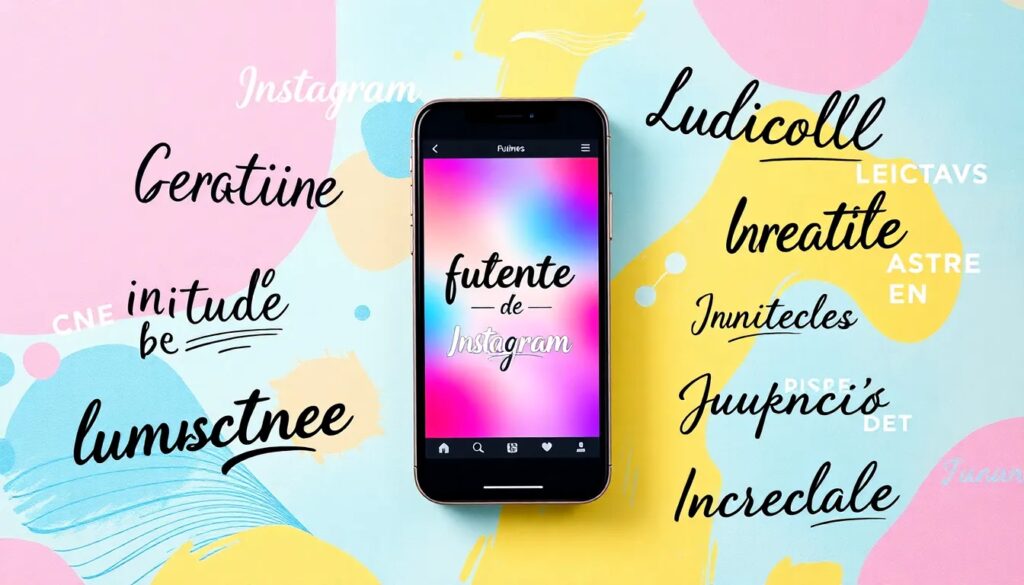
Instagram fonts: generador de fuentes para tus publicaciones
El uso de instagram fonts se ha convertido en una tendencia clave para quienes buscan destacar en esta red social. Las fuentes creativas no solo aportan un toque único a tus publicaciones, sino que también reflejan tu personalidad y estilo.
En este artículo, exploraremos todo lo que necesitas saber sobre las fuentes de Instagram, los generadores disponibles y cómo utilizar estos recursos para mejorar tu perfil y publicaciones.
¿Qué son las fuentes de Instagram?
Las fuentes de Instagram son variaciones tipográficas que los usuarios pueden utilizar para personalizar sus textos en esta plataforma. A través de diferentes estilos, puedes darle un aspecto más atractivo y único a tu contenido.
Estas fuentes se generan frecuentemente mediante caracteres Unicode, que permiten crear textos que simulan diferentes estilos de escritura. Esto incluye fuentes cursivas, negritas y otros efectos visuales.
Usar fuentes creativas en Instagram no solo mejora la estética de tu perfil, sino que también puede aumentar la interacción con tus publicaciones, ya que llamarán más la atención de tus seguidores.
¿Cómo funciona un generador de fuentes para Instagram?
Un generador de fuentes para Instagram es una herramienta que permite transformar texto ordinario en estilos tipográficos únicos. Simplemente ingresas el texto deseado y la herramienta te proporcionará diferentes opciones de fuentes.
La mayoría de estos generadores utilizan el estándar Unicode, lo que significa que los estilos generados son compatibles con diversas plataformas, no solo con Instagram. Esto facilita el uso de los textos en otras redes sociales o aplicaciones de mensajería.
El proceso es sencillo: ingresas tu texto, eliges el estilo que más te gusta y copias el resultado para pegarlo en tu perfil o publicaciones. Algunos generadores incluso ofrecen opciones de personalización más avanzadas.
¿Cuáles son las fuentes más populares para Instagram?
Algunas de las fuentes más populares para Instagram incluyen:
- Negrita
- Cursiva
- Contorno
- Versalitas
- Tachado
- Zalgo
Estas fuentes son ampliamente utilizadas porque añaden un toque especial a las biografías y publicaciones. Las fuentes cursivas y en negrita, por ejemplo, pueden hacer que ciertas palabras resalten más.
Además de estas opciones, muchos usuarios optan por combinar diferentes estilos para crear textos verdaderamente únicos. Experimentar con varias fuentes puede ser muy divertido y creativo.
Es importante recordar que no todos los estilos funcionarán en todas las áreas de Instagram. Por ejemplo, algunos estilos pueden ser filtrados o no mostrarse correctamente en comentarios.
¿Qué estilos de fuentes puedo usar en mi bio de Instagram?
En tu biografía de Instagram, puedes utilizar una amplia variedad de estilos. Algunos ejemplos incluyen:
- Fuentes cursivas: aportan elegancia y un toque personal.
- Negritas: ideales para destacar información clave.
- Fuentes en contorno: perfectas para un look moderno y minimalista.
- Estilos Zalgo: para un efecto más llamativo y divertido.
- Textos tachados: útiles para expresar ideas de manera creativa.
Elegir el estilo adecuado depende de la imagen que quieras proyectar. Combinar diferentes fuentes también puede dar lugar a resultados muy atractivos.
¿Por qué usar fuentes creativas en Instagram?
Utilizar fuentes creativas en Instagram puede marcar una gran diferencia en cómo los usuarios perciben tu perfil. Estas fuentes ayudan a que tu contenido se vea más profesional y atractivo.
Además, las fuentes únicas pueden aumentar la interacción y el engagement, ya que llaman la atención de tus seguidores. Esto es crucial en un entorno competitivo donde captar la atención es vital.